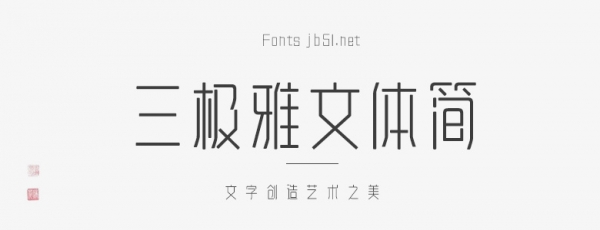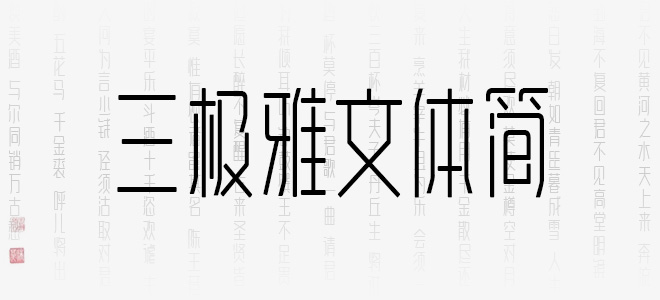
三极雅文体简是一款有着清新、文艺古典风的字体。这款字体的字面狭长,重心较高,用笔夸张,钩、捺特点明显。笔画镜像对称,折笔统一圆弧优雅,最大简化笔画形状,简洁时尚。字形清秀古朴、造型秀美惬意、点画呼应,新颖独特、纤细流畅。整体风格典雅质朴,秀丽端正艺术性较强。字形修长,简洁柔美,适用于文艺类广告和产品包装设计。
三极雅文体简